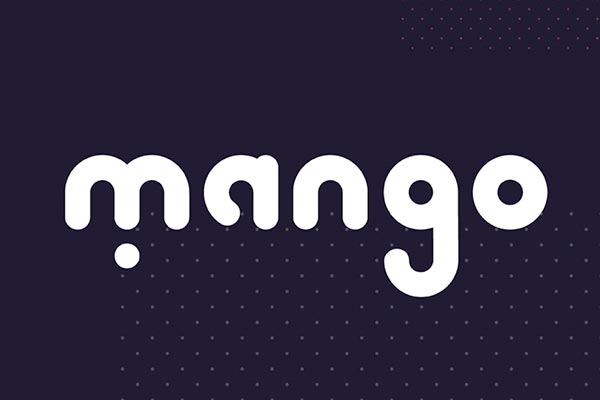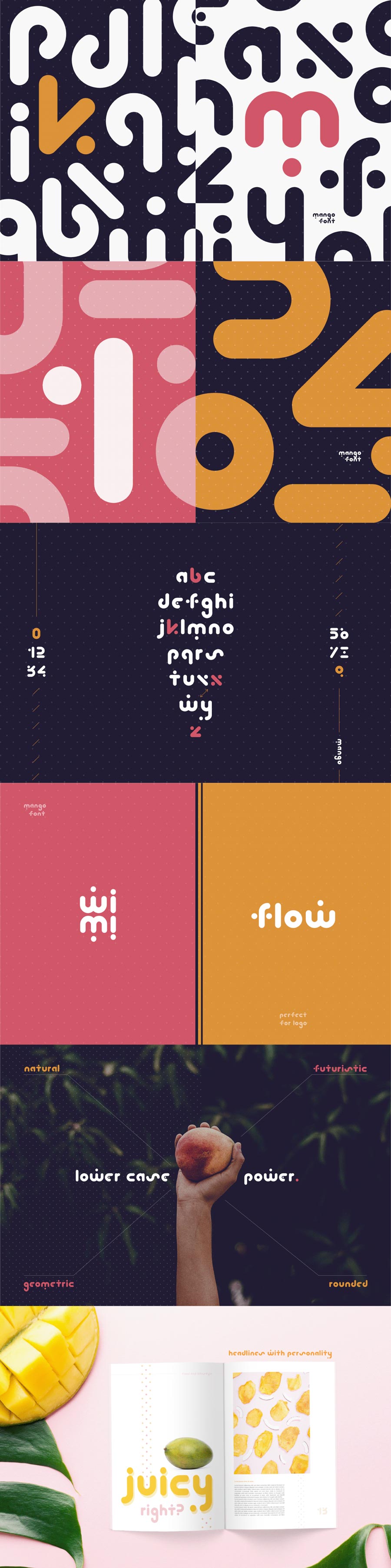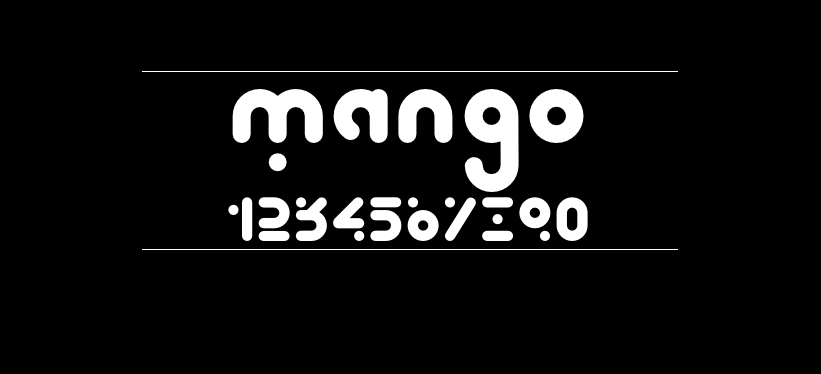
Mango
Mango字体介绍
Mango是由Daniele Franchi设计的一种免费的几何图形和最小的小写字体,以庆祝他在都柏林的创意机构Mango Media的新工作。这种新颖的未来字体包括独特的字符集以及一些壮观的干净字母。非常适合与未来相关的任何现代设计项目,并且非常适合原始徽标,标题和动态图形动画。
Mango字体应用示例